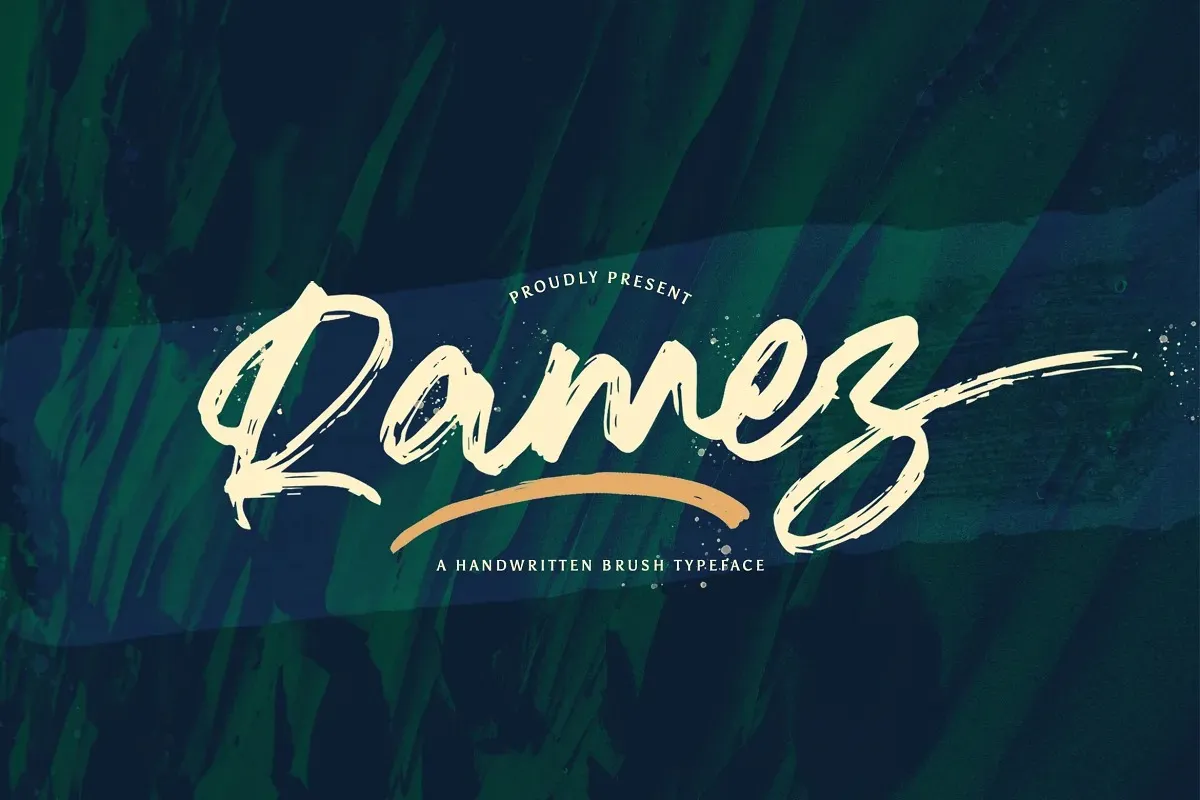
Ramez Font – Download Grátis
A fonte Ramez é uma autêntica fonte cursiva criada por StringLabs. Suas linhas suaves e desenhos casuais proporcionam um ar de casualidade perfeitamente apropriado para qualquer contexto. Este design versátil, com aparência levemente terrestre e muito fácil de ler, fará sua marca brilhar em qualquer situação, seja ela inserida num fundo colorido ou usada como uma grande aposta na seção principal do seu site. Com o Ramez você pode adicionar um toque especial a qualquer projeto gráfico, tornando-o único e inovador.